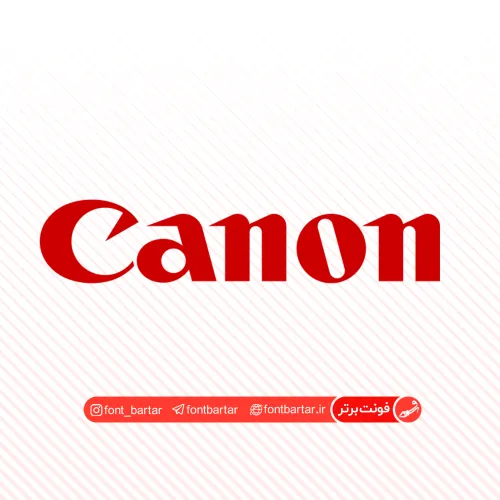
فونت انگلیسی canon
فونت استفاده شده در لوگو تایپ لوازم الکترونیک CANON ،این فونت در دسته فونت های انگلیسی به حساب میاید و همچنین ساختار این فونت باعث شده جز فونت های کاربردی نیز قرار بگیرد با ساختار و چینش آشنا برای همگان ، هم اکنون بصورت رایگان از فونت برتر در دسترس است.
فونت انگلیسی canon مورد استفاده برای: